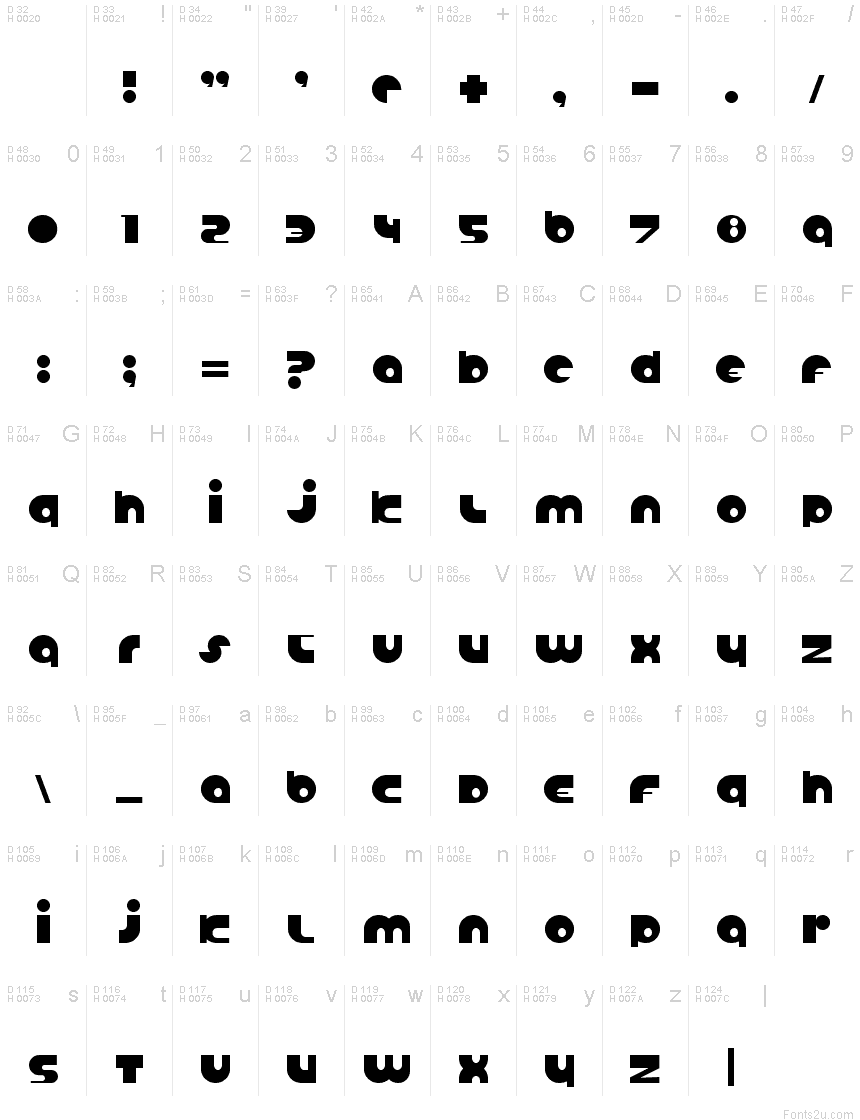
خط Anabolic Spheroid من Levi هو خط عرض (display) مجاني ومميز، يتميز بحروف تشبه الفقاعات اللامعة المحبوسة في شبكة محكمة. تبدو كل منحنية وكأنها منتفخة ومضغوطة، مع أشكال دائرية ضخمة ومدمجة بعناية داخل إطارات مربعة. والنتيجة هي إيقاع جريء ومرح يسهل قراءته، مع منح شعور بالانتفاخ يشبه ملصقات الفينيل أو لافتات البلاستيك الطرية.
باستخدام خط Anabolic Spheroid، تكتسب العناوين على الفور طابعاً ريترو مستقبلياً جذاباً يلفت الانتباه دون صراخ. هذا الخط المجاني يبرز بوضوح على ملصقات الحفلات، ومنشورات الموسيقى، وعلامات الأطفال التجارية، وعناوين الألعاب، والشعارات الجريئة، وتصاميم شبكات التواصل الاجتماعي حيث ترغب في ترك انطباع دائري وودي. جرب تنسيقه مع خط sans هندسي نظيف وخفيف للنص الأساسي، واحرص على استخدام Anabolic Spheroid بحجم كبير لتبقى تلك الأشكال الفقاعية واضحة ومقروءة.